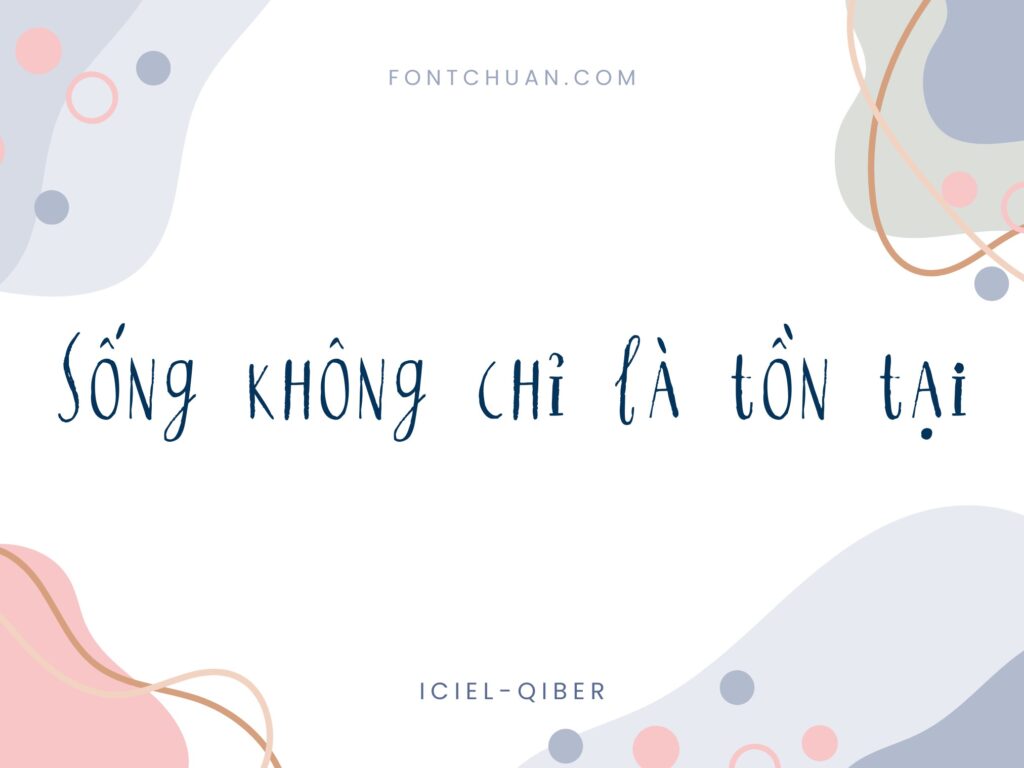
Font iCiel Qiber Việt Hóa
Qiber là một kiểu chữ viết tay cô đọng với phong cách độc đáo và cá tính, được thiết kế bởi Mariya V. Pigoulevskaya và phát hành bởi The Northern Block vào năm 2014. Font này mang lại cảm giác thân thiện và vui tươi, nhờ sự kết hợp giữa các ký tự viết hoa nhỏ trong bộ ký tự viết thường. Đặc biệt, Qiber đã được Việt hóa bởi iCiel, hỗ trợ tiếng Việt cùng nhiều ngôn ngữ khác, đáp ứng nhu cầu đa dạng của người dùng. Thành viên của Font Chuẩn đã sưu tầm và chia sẻ font này, giúp cộng đồng thiết kế ứng dụng dễ dàng trong các dự án của mình.
Về đặc điểm thiết kế, Qiber sở hữu 475 ký tự với kerning được chỉnh sửa thủ công và một loạt các họa tiết trang trí, tạo nên sự linh hoạt cho nhiều ngữ cảnh sử dụng. Font này phù hợp cho các thiết kế như tiêu đề, poster, logo, bao bì sản phẩm và các ấn phẩm truyền thông cần sự nổi bật và cá tính. Ngoài ra, Qiber còn thích hợp cho các ngành nghề như quảng cáo, ẩm thực, thiệp cưới và spa, cùng các sự kiện đặc biệt như lễ hội, sinh nhật, Halloween và Trung thu.